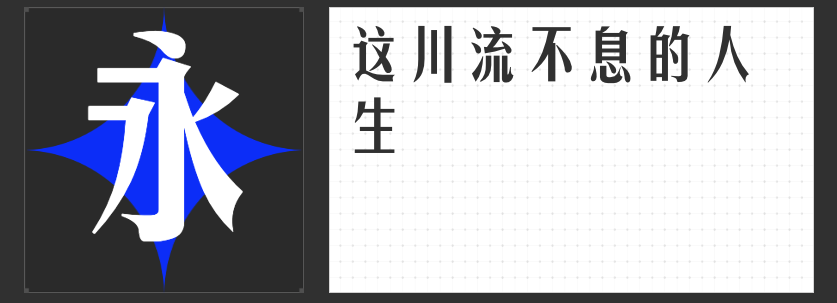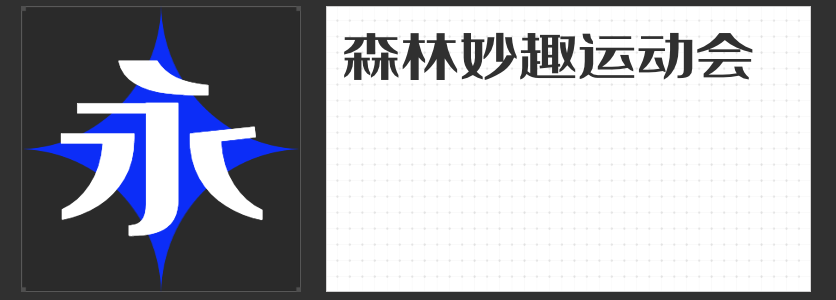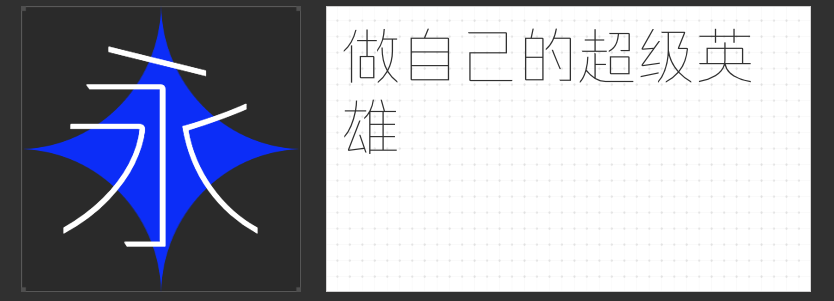
商务办公必备:四款高效字库字体推荐
在繁忙的商务办公环境中,一份清晰、专业的文档往往能够给人留下深刻的印象。而选择恰当的字体,则是提升文档品质的关键一步。今天,我将为大家推荐四款专为商务办公设计的字体,它们各具特色,能够满足不同场景下的需求。
这款字体以黑体为基础,通过斜切的起收笔方式,将部分笔画进行了简化和省略,营造出一种清透柔和的美感。选择最为纤细的笔画字重,使得整体字体看起来更加轻盈、优雅。在需要展现细腻、精致感的商务文档中,这款字体无疑是一个绝佳的选择。
2.励字美黑简
融合了黑体与宋体的优点,励字美黑简字体匀称、清秀美观,给人端正又正气的视觉效果。在正式的商务报告、合同文件等场合,这款字体能够彰显出文件的正式性和专业性,同时也易于阅读,减少了读者的阅读负担。
3.励字魔方黑简
字形方正、简洁无装饰,横竖笔形粗细视觉对比明显,笔形方头方尾,励字魔方黑简以其独特的风格脱颖而出。这款字体非常醒目,能够迅速吸引读者的注意力,适用于需要强调重点信息的商务文档。同时,其广泛的适用性也使得它成为许多商务人士的首选。
4.高手兵克高级黑
高手兵克高级黑以其沉稳、大气的风格著称。这款字体线条流畅、结构紧凑,透露出一种力量感和稳重感。在需要展现权威、专业的商务场合,高手兵克高级黑无疑是一个值得信赖的选择。
综上所述,这四款字体各具特色,能够满足商务办公中的不同需求。选择适合自己的字体,不仅能够提升文档的品质,还能够展现出个人的专业素养和审美品味。